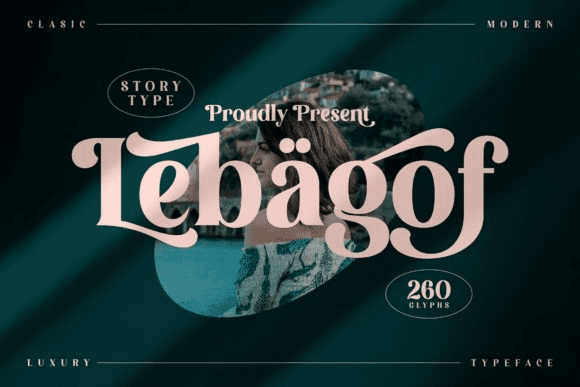
Название: Lebagof Font (2021)
Lebagof - смелый, стильный и толстый шрифт с засечками.
Название: Lebagof Font (2021)
Lebagof - смелый, стильный и толстый шрифт с засечками.